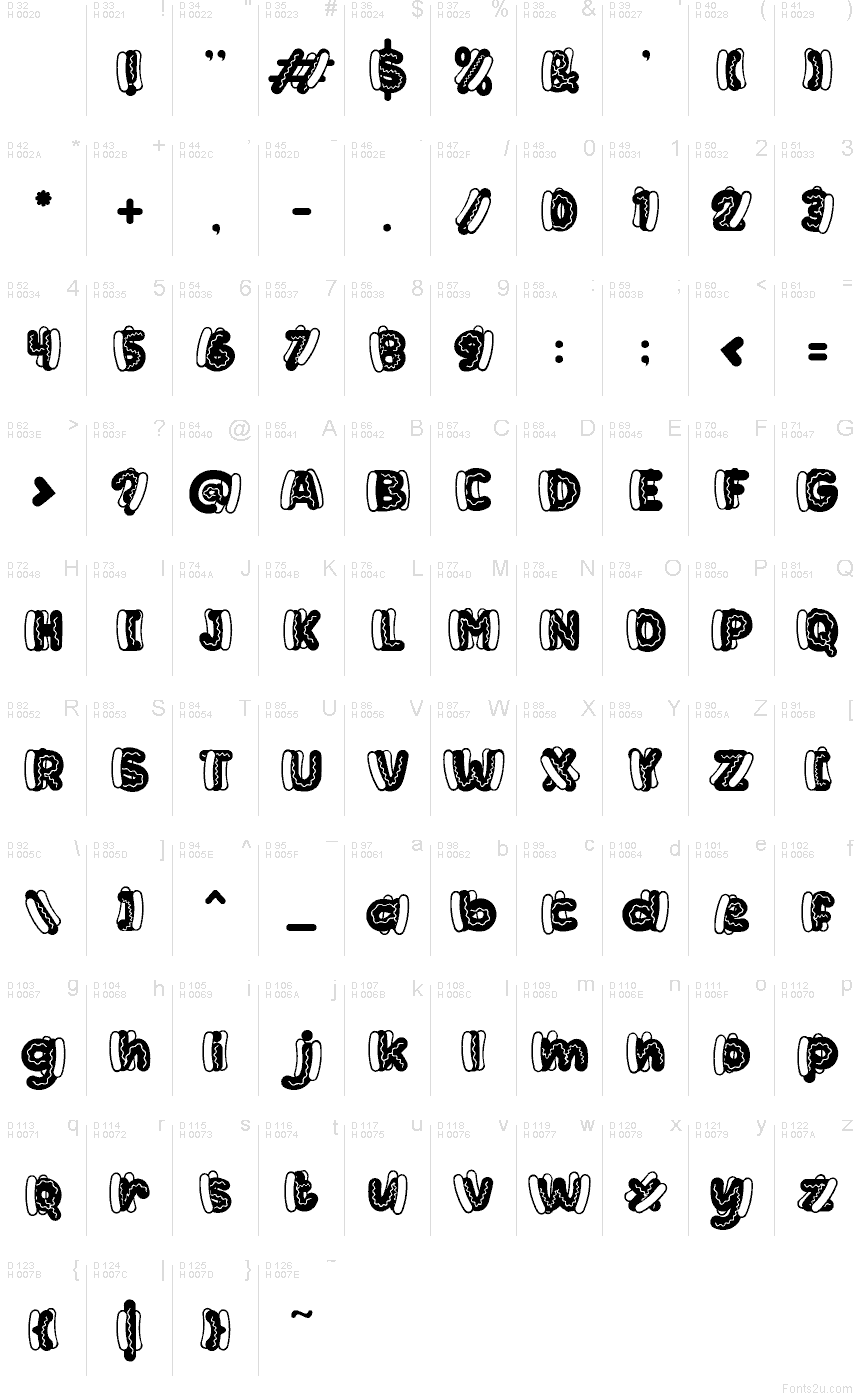
Smoky Maple Eight od Putracetol Studio to darmowy, psychodeliczny krój display typu blob. Jego napuchnięte, kreskówkowe litery wyglądają, jakby były zanurzone w syropie i otoczone grubym, wyraźnym obrysem. Faliste wycięcia i obłe kształty nadają krojowi rytmiczny, „topiący się” charakter, dzięki czemu całość prezentuje się zabawnie, oryginalnie i w stylu retro, zamiast być tylko dekoracją.
Sprawdzi się idealnie na opakowaniach słodyczy, plakatach dla dzieci, w projektach naklejek, na okładkach muzycznych czy w krótkich nagłówkach w mediach społecznościowych, gdzie darmowy font z tak dużą dawką „płynnego” ruchu potrafi samodzielnie zbudować klimat. Użyj go, gdy chcesz, aby litery same w sobie były ilustracją – szczególnie w krótkich hasłach i nagłówkach typu logo, gdzie te drgające kontury robią największe wrażenie.